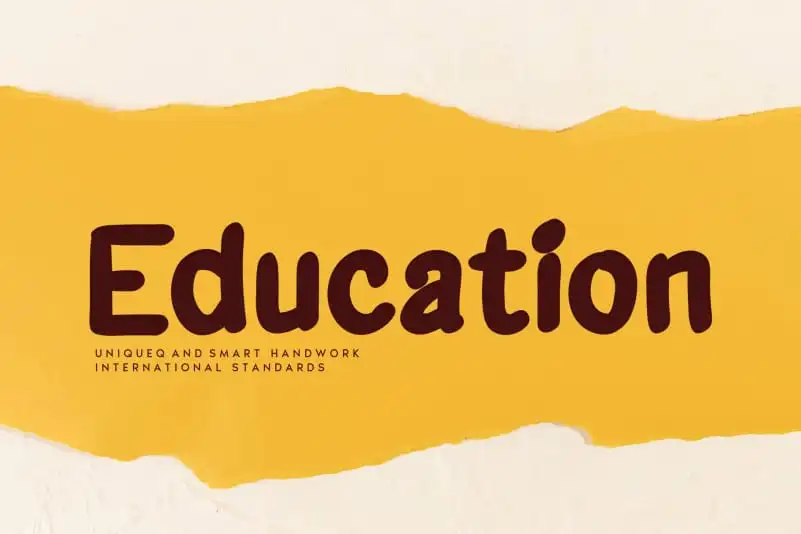
Education Display Font – Fonte Grátis
Education Display Font
A Educação Display Font é uma fonte de escrita manuscrita ideal para projetos educacionais e acadêmicos. Introduzida pela andikastudio, esta fonte oferece um conjunto único e criativo que vai além do básico. Perfeita tanto para lembretes escolares quanto para design em cartazes e materiais didáticos, a Educação Display Font destaca-se por sua riqueza de detalhes e seu poder de transformar qualquer texto em uma verdadeira obra de arte. Ideal para professores ou designers que buscam estilizar seus trabalhos de maneira única e profissional, esta fonte é perfeita para criar cartazes didáticos, flyers educacionais, materiais de sala de aula ou até mesmo capas de livros escolares. Além disso, o design manuscrito proporciona um toque familiar e reconfortante, mantendo-se fiel à essência da educação enquanto adiciona um toque distintivo ao material. A andikastudio tem se destacado com sua abordagem criativa em cada produto lançado, oferecendo soluções de design para atender a uma ampla variedade de necessidades. Com a Educação Display Font, eles continuam a trazer inovação e beleza aos ambientes escolares e acadêmicos, tornando as experiências de aprendizado mais memoráveis e atraentes.